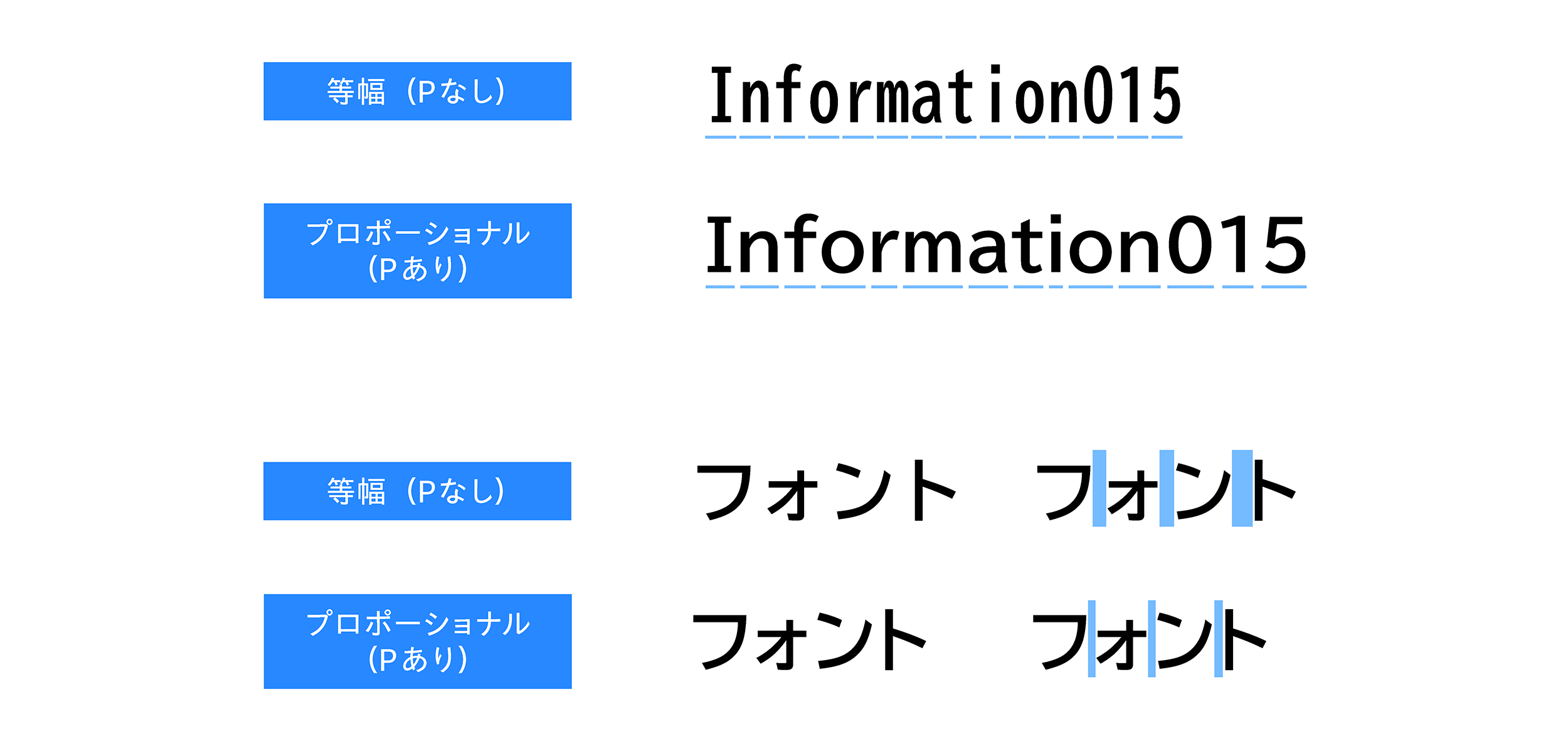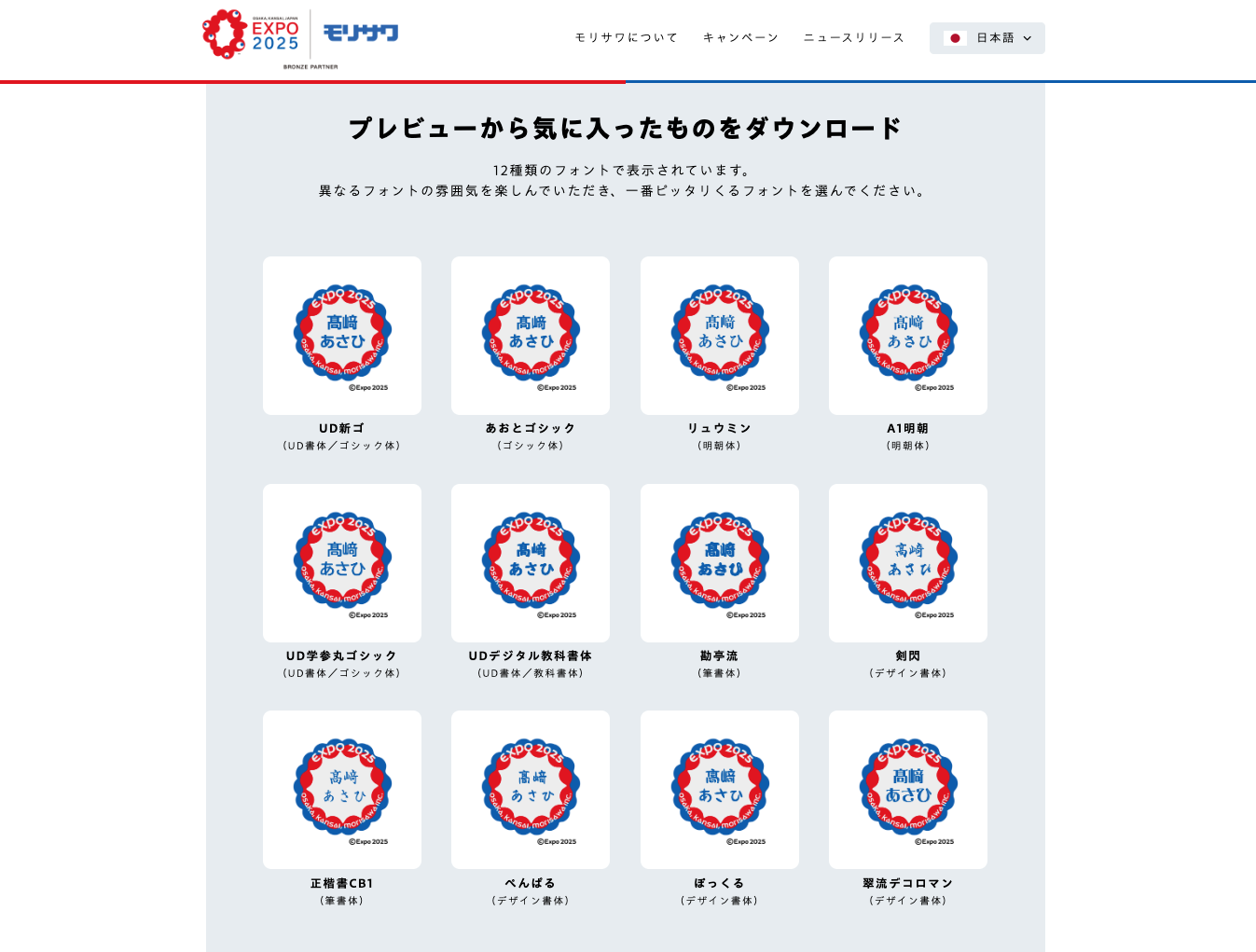
モリサワ フォントの意識調査を実施 働く男女の約半数がシチュエーションによってフォントを使い分け、プレゼン資料、報告書、謝罪文などビジネスシーンで選ばれるフォントとは
モリサワは「大阪・関西万博PRブロンズパートナー」として協賛しており、これを記念して開設した大阪・関西万博特設サイトを公開中です。その中で、フォントを使ってデジタルスタンプを作成できる「フォント de スタンプ」などのフォントを使ったコンテンツを公開中です。本調査はこれらの活動の一環で実施したもので、デザインなどの専門的な職種に限定しない働く男女を対象とし、フォントをツールやシチュエーションによって変えているかや、好みのフォントが決まっているかなどについて調査しました。
️フォントにこだわりがあるか、ツールによって使い分けているか
フォントにこだわりや気に入っているフォントがあるか聞いたところ、「ある(16.0%)」、「どちらかといえばある(26.6%)」と回答した人を合わせて4割以上の人がフォントにこだわりを持っていることがわかりました。
また、メールやSNS、仕事で使うツールなどにおいて、デフォルトのフォントから自分好みのフォントに変えているか調査したところ、「基本変えている(18.0%)」、「ものによるが変えている(29.2%)」と、半数近くの人が自分好みのフォントにカスタマイズしていることがわかりました。
フォントを自分好みのものに変えている人にその理由を聞いたところ、「自分好みのフォントの方が見やすいから(66.5%)」、「好みのフォントがあるから(33.9%)」、「変えたフォントの方が適していると思うから(26.3%)」が上位となる結果でした。
シチュエーションによってフォントを使い分けているか、各シチュエーションで適切だと感じるフォントは
プレゼン資料、謝罪文など、さまざまなシチュエーションに応じてフォントを使い分けているのかも調査しました。その結果、「使い分けている(20.2%)」、「どちらかといえば使い分けている(24.8%)」を合わせて45%と、半数近くの人が状況に応じてフォントを使い分けていると回答しました。年代別では、フォントを使い分けている人は20代で47.2%、30代で51.2%、40代で38.4%、50代で43.2%でした。比較的若年層の方が、フォントを使い分けている人が多い傾向にありました。
また、実際にどのフォントを使うのが適切だと思うかシチュエーション別で回答してもらったところ「謝罪文書」「ビジネスメール」「プレゼン資料・企画書・報告書」「社内報」「財務資料」といったビジネスシーンでは「明朝体」に最も多く票が集まりました。ビジネスシーン以外の「LINEなどSNS」「TVのテロップ」では、「明朝体」のほか「ゴシック体」「丸ゴシック体」「UD書体」「デザイン書体」「装飾書体」「手書き書体」などにも票が分かれる結果になりました。また「看板・チラシ・推し活のうちわ等祭事・催し事関連」においては「デザイン書体(33.0%)」「丸ゴシック体(30.6%)」「YouTubeなど動画コンテンツ」においては「手書き書体(38.8%)」「装飾書体(35.8%)」など、比較的ポップな印象のフォントが適切だと感じる人が多い傾向にあることがわかりました。
さらに、文章とフォントが合っていないなど、フォントに対して違和感を覚えたことはあるかも調査をしました。「あてはまるものはない」と回答したのは67.2%で、全体の32.8%、つまり約3人に1人は、違和感を覚えたことがあるようです。違和感を覚えたことがあるシチュエーションについて調査したところ、1位は「ビジネスメール(36.0%)」、次いで「謝罪文書(32.3%)」、「プレゼン資料・企画書・報告書(24.4%)」という結果でした。どんな違和感を覚えたのか具体的に聞くと、「ビジネスのメールにも関わらず遊びに使用するようなフォントで誠実さが伝わらない(神奈川県・44歳女性)」、「謝罪文でポップな文字が使われており誠意が伝わらなかった(青森県・38歳男性)」などの声が寄せられました。
️好きなフォント(男女別・年代別)
好きなフォントの分類について聞いたところ、最も多かったのは「明朝体(35.2%)」で、2位は「ゴシック体(18.8%)」、3位は「手書き書体(14.4%)」でした。「明朝体」が好きな理由としては「最も見慣れているから」「一番見やすく無難」「上品で誠実なイメージがあるから」といった声が寄せられました。「ゴシック体」は「シンプルでどこでも使える」「見やすく誰でも読みやすい」「かたすぎず、砕けすぎていないから」、「手書き書体」は「可愛らしいが読みやすい」「アナログで書いたような温かみがあるから」「温かみと愛嬌があり柔らかい印象を受けるから」との声が集まりました。
好きなフォントランキング (n=500) | |
1位 |
明朝体(35.2%) |
|
2位 |
ゴシック体(18.8%) |
|
3位 |
手書き書体(14.4%) |
|
4位 |
UD(ユニバーサルデザイン)書体(9.8%) |
|
5位 |
丸ゴシック体/筆書体(9.4%)※同率 |
|
7位 |
デザイン書体(2.2%) |
|
8位 |
装飾書体(0.8%) |
男女別でみると上位3位のランキングは全体と同じでしたが、4位は男性では「筆書体(11.2%)」、女性は「丸ゴシック体(12.8%)」でした。年代別では、1位は「明朝体」、2位は20代・30代が「ゴシック体(20代:25.6%、30代:24.8%)」、40代が「手書き書体(16.0%)」、50代が「UD書体(17.6%)」と年代によって好みが分かれる結果となりました。
️「フォント de スタンプ」で使えるフォントの中で最も知名度が高いのは
モリサワの大阪・関西万博特設サイトでは、フォントを選んで作れる!「フォント de スタンプ」を展開しており、大阪・関西万博モチーフのデザインを含むフレーム(台紙)とモリサワの12種類のフォントを使って、ご自身の好きな言葉やお名前を入力したオリジナルデジタルスタンプ(スタンプ形式のデジタル画像)を作成、ダウンロードすることができます。今回の調査では、スタンプで使用できるフォントの中から一部のフォントについて、フォント名を記述式で回答してもらいました。その中で最も正答率が高かったのは推し活うちわの文字などに人気の「勘亭流」でした。この機会にぜひフォントの名前を覚えていただき、勘亭流など12種類のフォントを使ったオリジナルデジタルスタンプを作ってみてください。
️フォントの知識について
「BIZ UDゴシック/BIZ UD Pゴシック」など、フォントには「P」がついているものとそうでないものがあります。Pなしのフォントは等幅フォントで、かな・漢字は全角、英数は半角の等幅で表示されますが、P付のフォントは“プロポーショナルフォント”と言い、英数やかなの文字幅が文字の形によって異なります。この違いを知っているか聞いたところ、「知っている(3.6%)」と回答した人は1割にも満たない結果となりました。「なんとなく使い分けているが、違いはよく知らない(33.2%)」は約3割いました。フォント自体の存在を知っている人は一定数いるものの、フォント名の認知度と同じように、フォントに関する専門的な知識は大多数の人が持っていないことがわかりました。
モリサワと大阪・関西万博について
モリサワは「大阪・関西万博PRブロンズパートナー」として協賛し、大阪・関西万博の会場サインやアプリなどで使用するための各種フォントも提供しています。また、「大阪ヘルスケアパビリオン Nest for Reborn」のサポーターとして、展示ディスプレイや平面サインなどで使用されるフォントを提供しているほか、その他のパビリオンでも各種フォントを採用いただいています。
モリサワのUDフォントについて
モリサワのUDフォントは、「文字のかたちがわかりやすいこと」「文章が読みやすいこと」「読み間違えにくいこと」をコンセプトに開発されています。具体的には、濁点や半濁点を大きくして、区別をつけやすくしているほか、シルエットの似た文字を判別しやすくするために、はなれを明確にするなどの工夫をしています。第三者機関と共同で可視性・可読性に関する比較研究報告も実施しています。